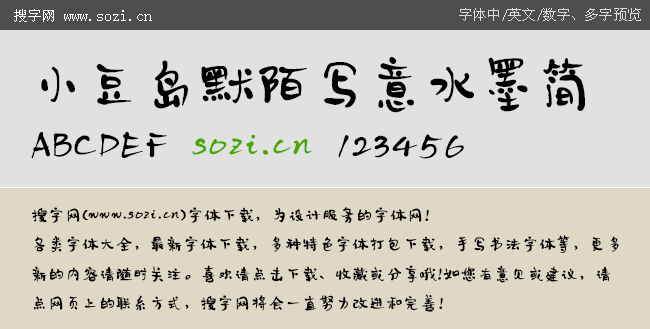
小豆島默陌寫意水墨簡
搜字網(wǎng)提供一款小豆島默陌寫意水墨簡中文字體下載,小豆島默陌寫意水墨簡體是一款非常有趣手寫卡通字體,這款字體筆劃間帶有水墨風(fēng)格,字形活潑可愛,充滿童趣,適合應(yīng)用于兒童廣告設(shè)計、卡通包裝設(shè)計、趣味海報、產(chǎn)品設(shè)計等應(yīng)用。